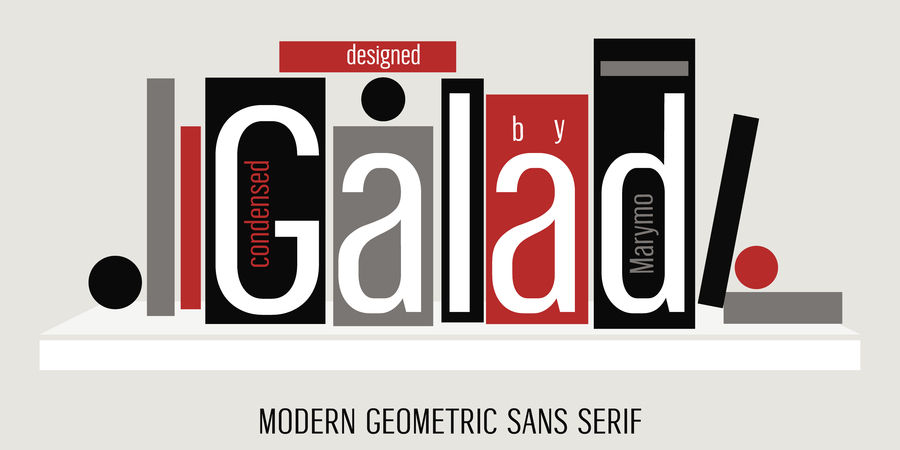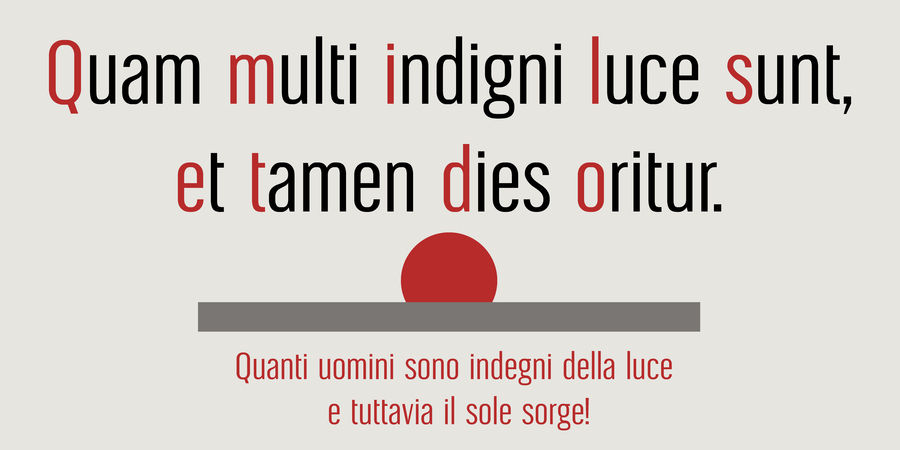
Galad – вузький ґротеск. Його розробка почалася в 2017 році на курсі "Геометричний ґротеск" під керівництвом Кирила Ткачова. Шрифт поєднує риси, притаманні геометричним та гуманістичним шрифтам без зарубок, має помітний контраст та напівзакриті форми.
Galad призначений для заголовків, реклами, плакатів та невеликих уривків тексту. Шрифт розробила Марчела Можина у 2018 році.
рівний, стиснений, статичний, високий, серйозний, дорослий, міський, стійкий, стабільний, твердий, гучний, вузький, впевнений, якісний, точний, чіткий, архітектурний, сучасний, стрункий, діловий, формальний